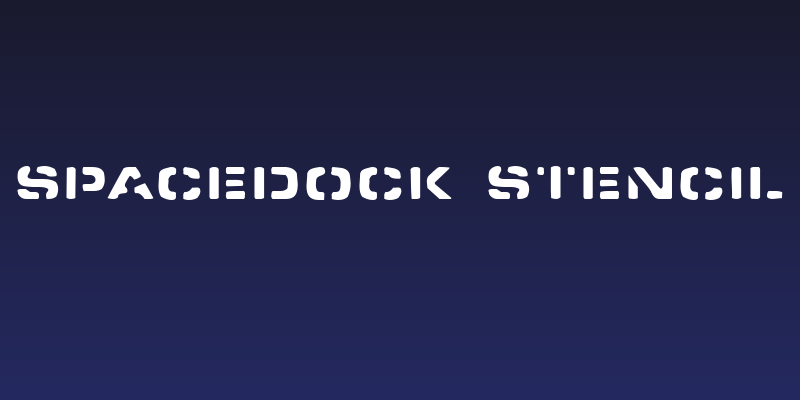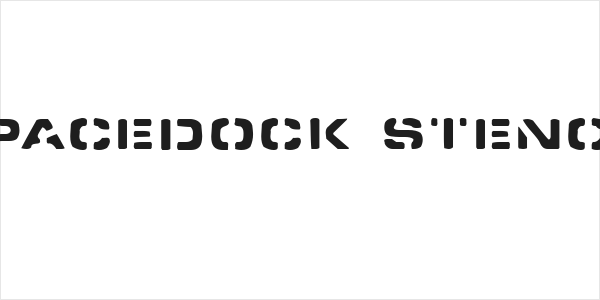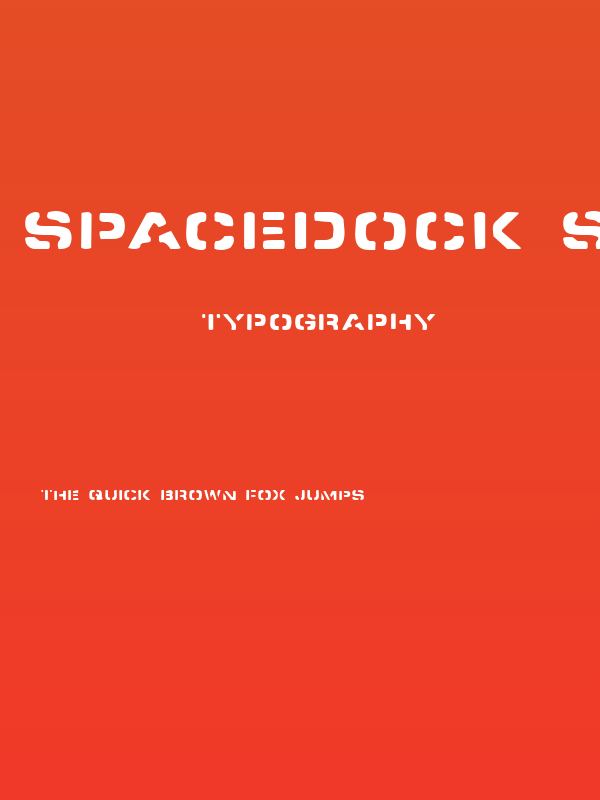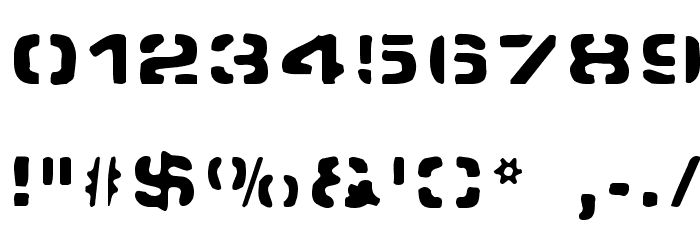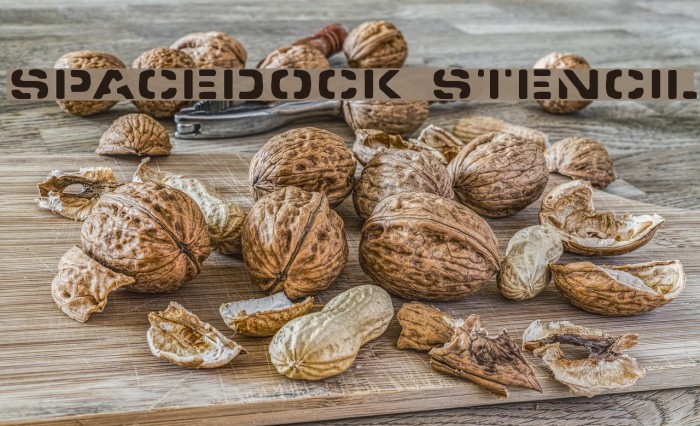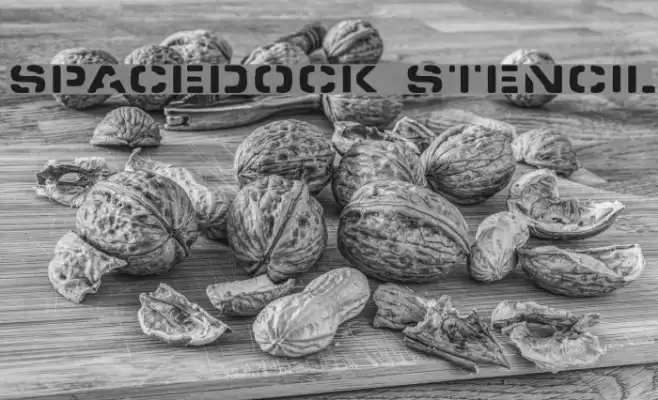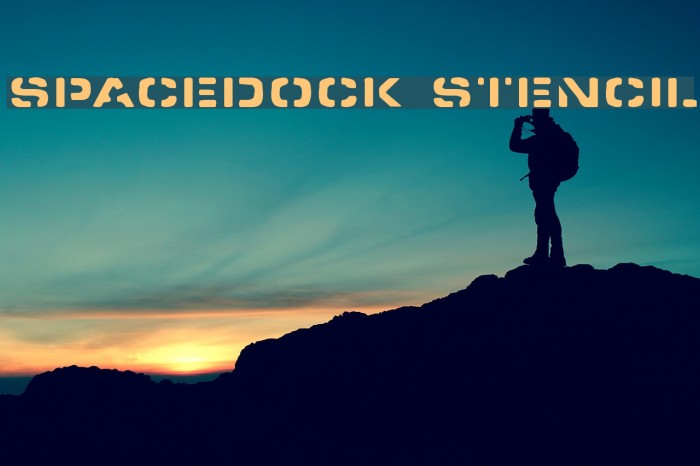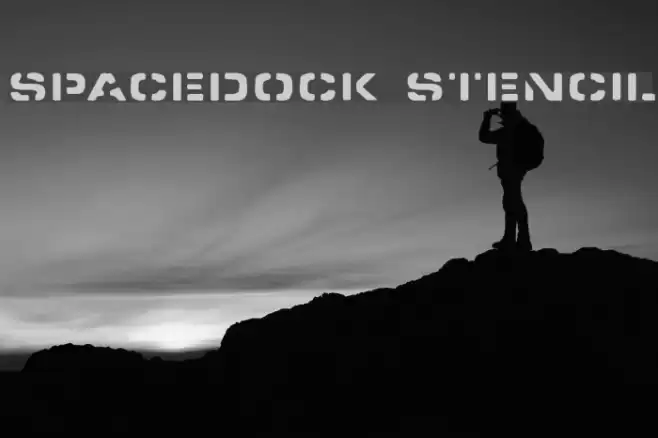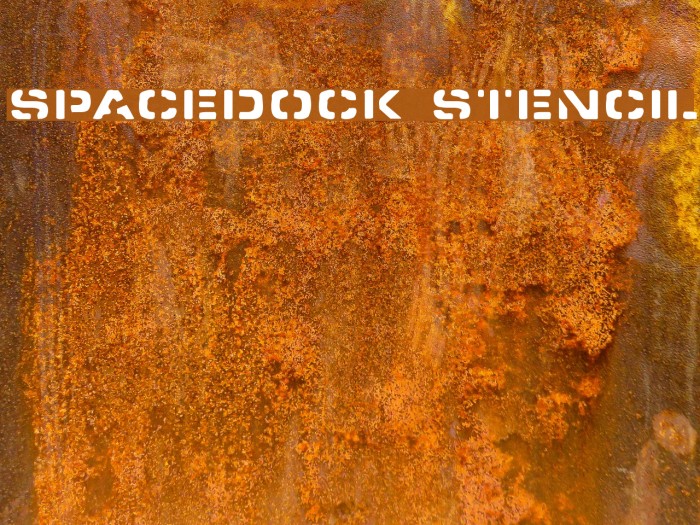
Spacedock Stencil Font
| النمط العام | Futuristic, Industrial |
| مشاريع مقترحة | Ideal for sci-fi themed designs, military posters, branding for tech companies, and video game titles. |